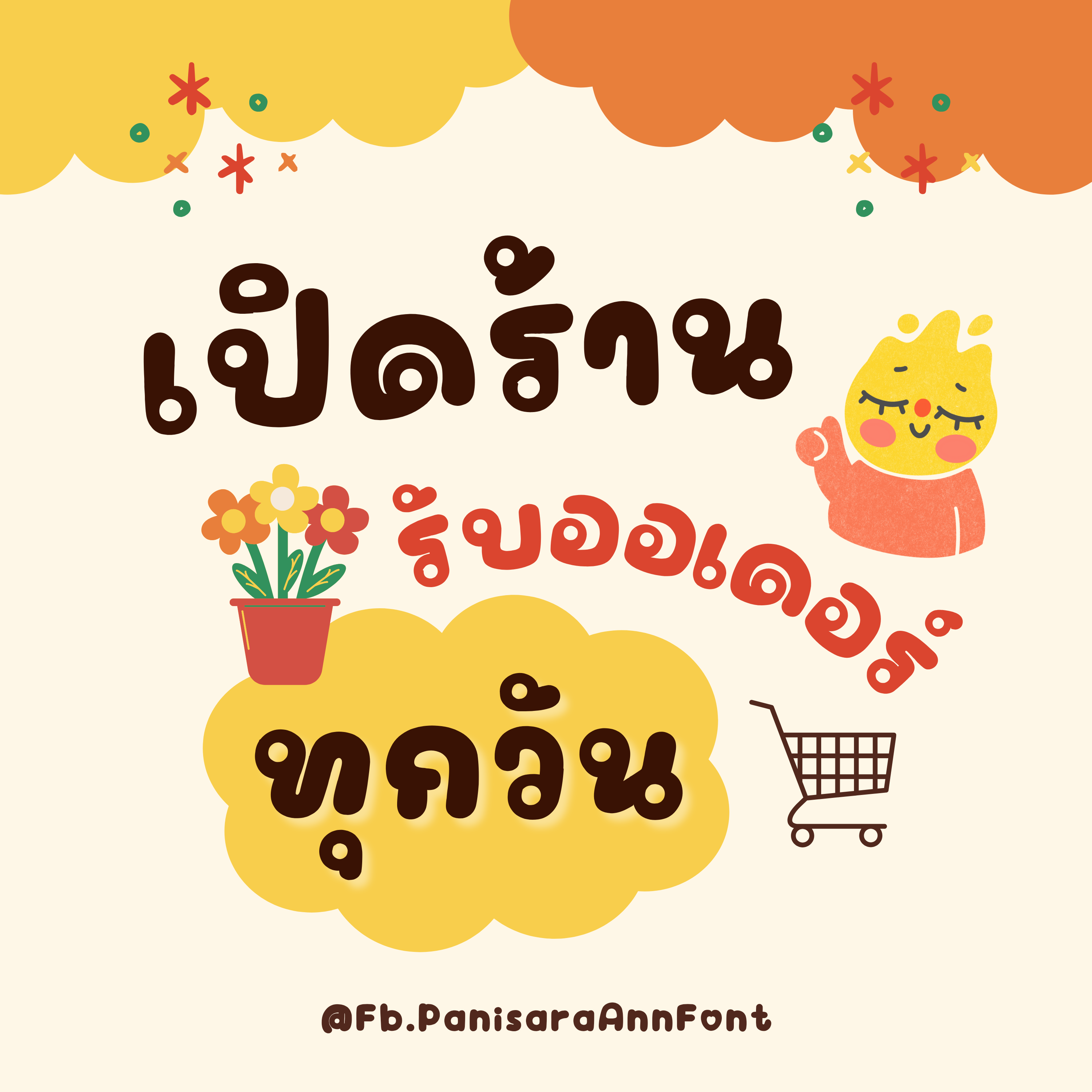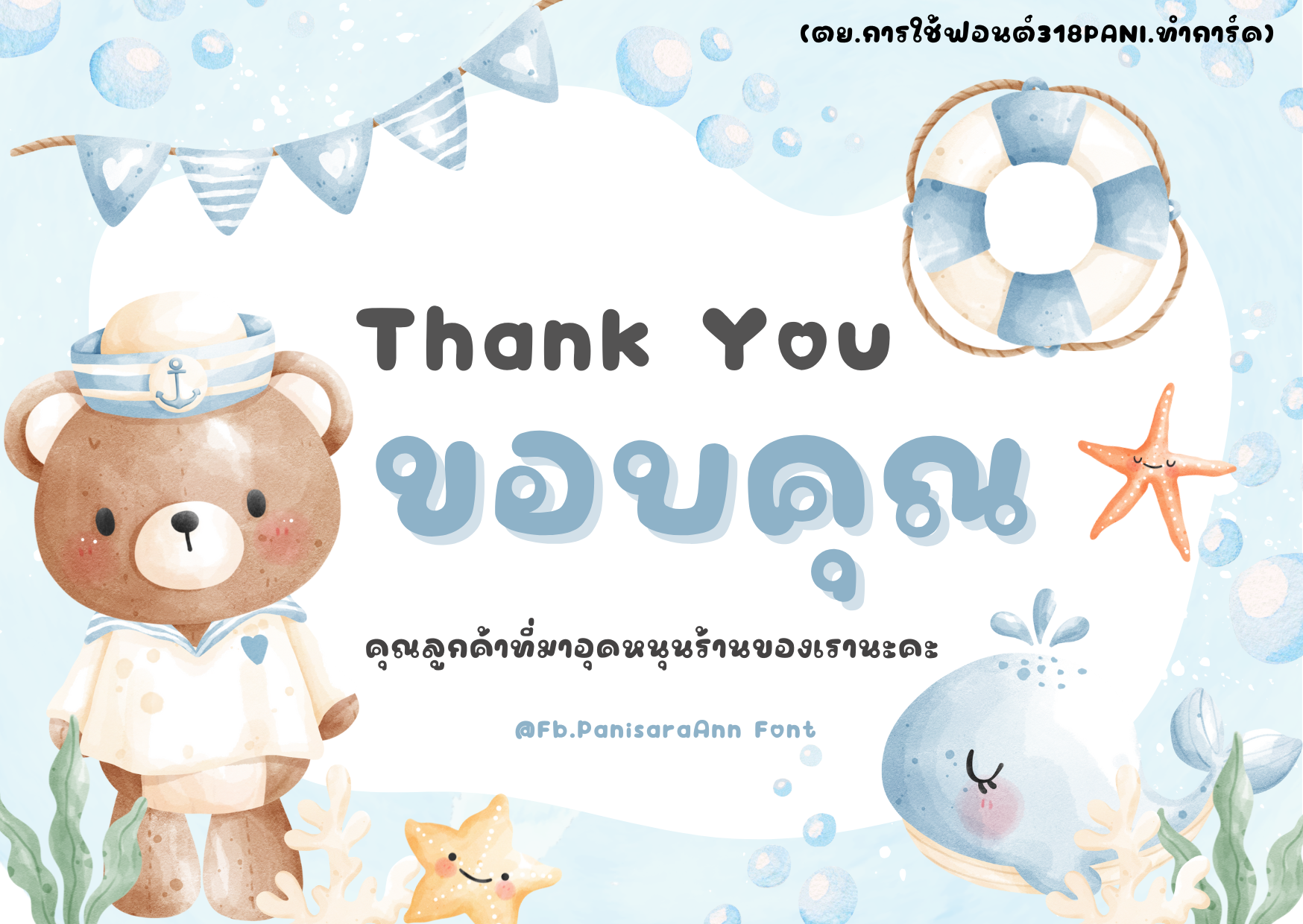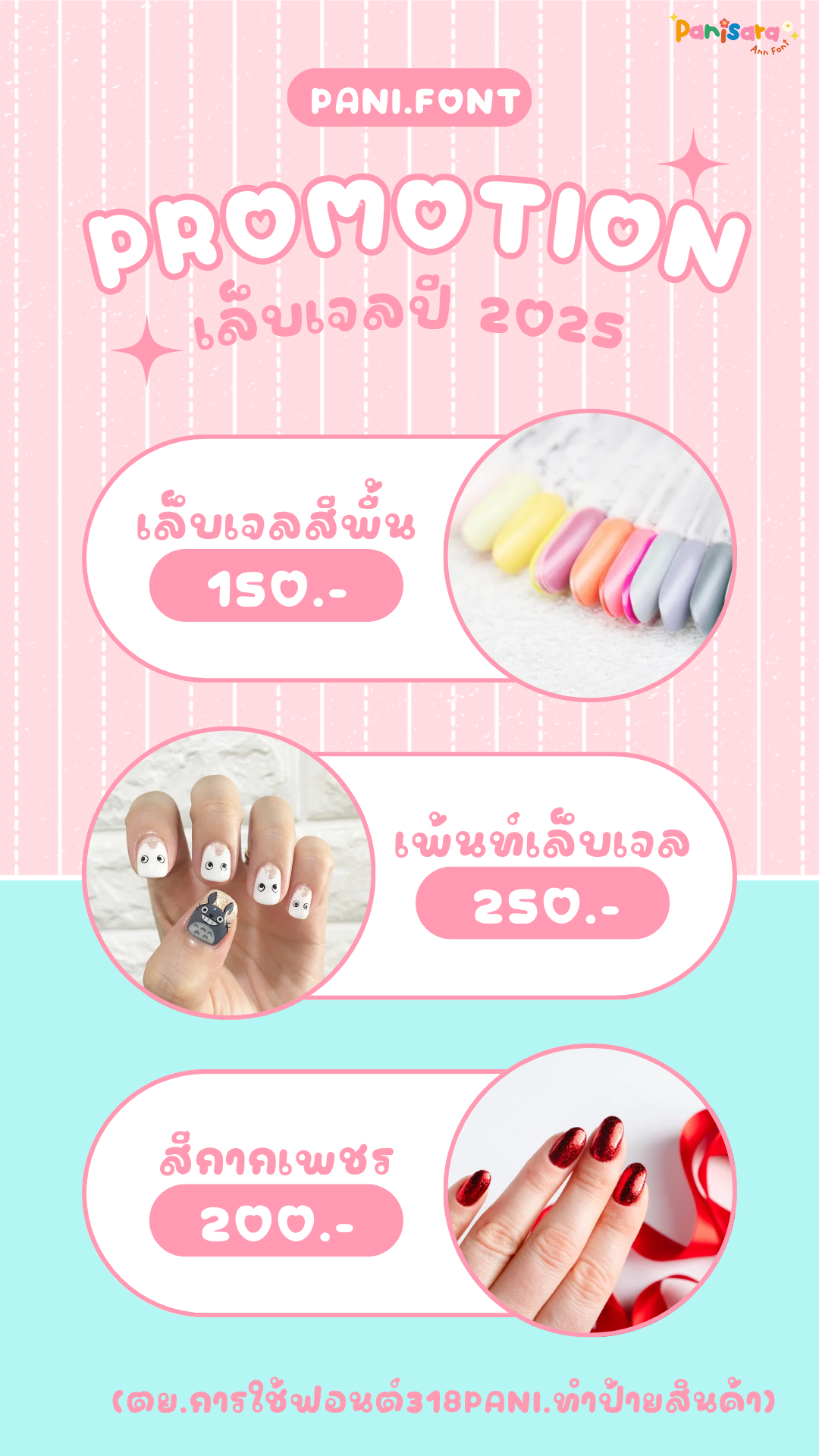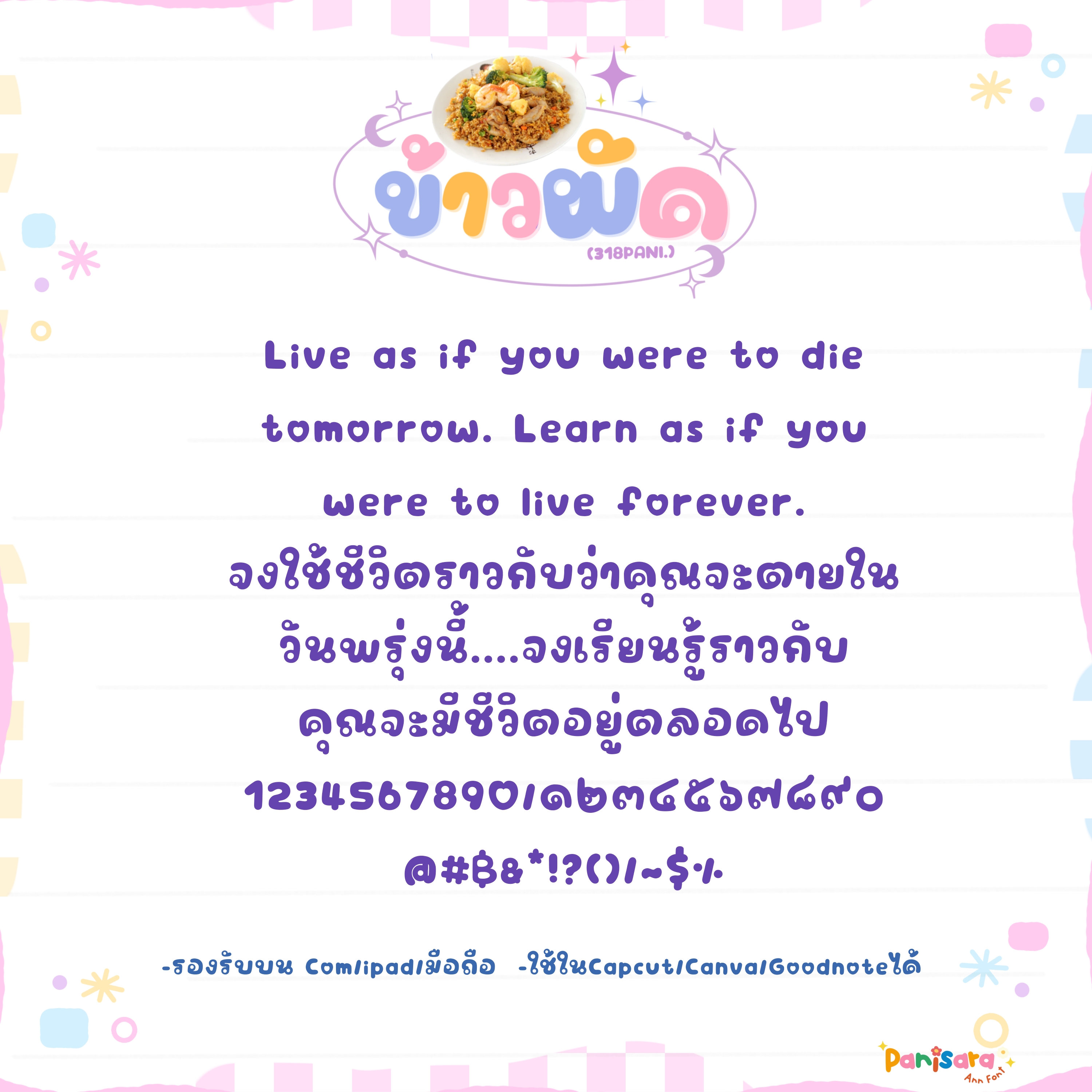
ฟอนต์ 318PANI.ข้าวผัด
PANI.
ฟอนต์ 318PANI.ข้าวผัด แจกฟรี!! ตัวDemo
ฟอนต์ตัวเข้ม อ่านง่าย ทันสมัย
เหมาะจะใช้เป็นหัวข้อ สวยเด่น
หรือใส่เลขตอนขายสินค้าก็ดูชัดเจน
ตัวอย่างการใช้ฟอนต์แต่งภาพใน Canva